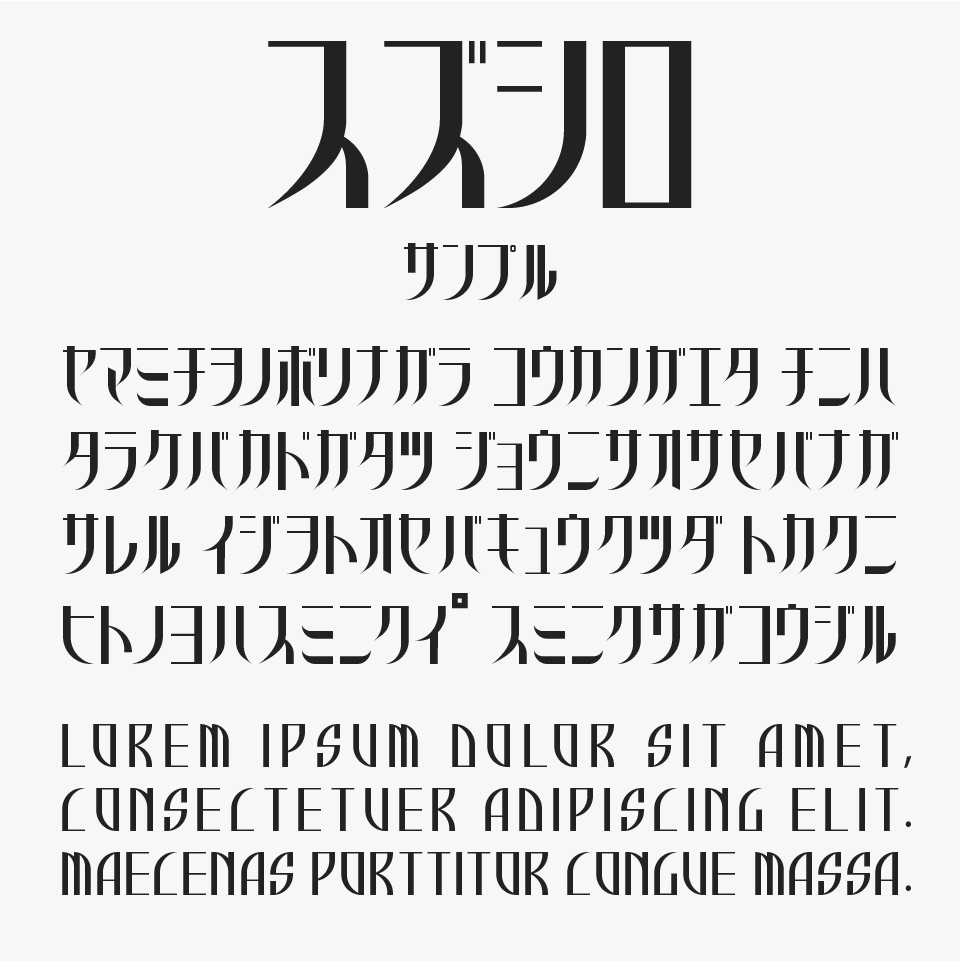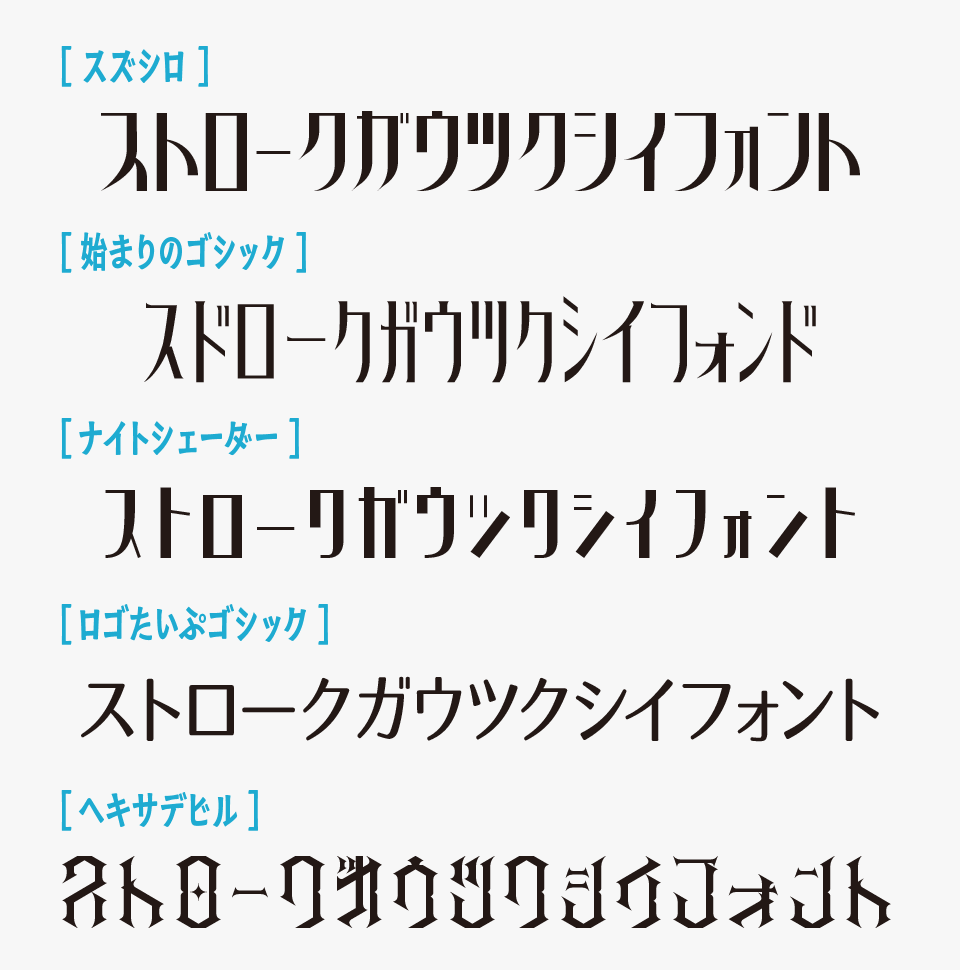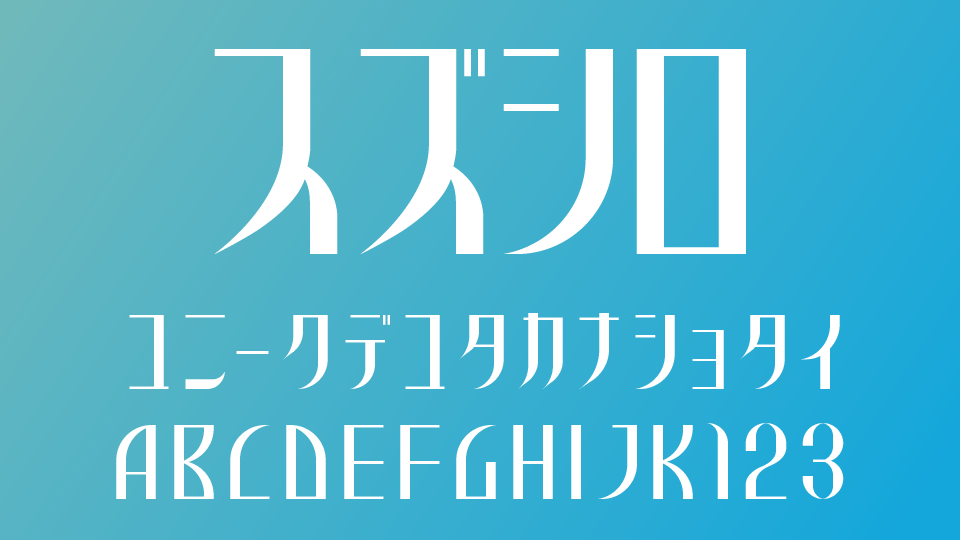
スズシロフォントは、シャープで縦長のプロポーションと鋭い切れ込みが特徴的な、アールデコ調の雰囲気を感じさせるデザインフォントです。
細い線と太い線のコントラストが美しく、文字全体に洗練された雰囲気を感じられるフォントです。幾何学的でありながらどこか優雅さもあり、クラシカルな空気と未来的な印象がミックスされたようなデザインがとてもステキです。
映画タイトルや漫画ロゴや高級感のあるパッケージ、レトロモダンなビジュアルなどと相性が良く、フォントそのものでロゴが完成してしまうようなフォントです。都会的でミステリアスな空気をまとった、個性的なフォントです。
スズシロフォントを、ほかのシャープなスタイルを持つカタカナフォントと比較してみると、鋭さの中にある軽やかさや洗練された雰囲気が魅力のフォントです。
比較フォントは、「始まりゴシック」「ナイトシェーダー」「ロゴたいぷゴシック」「ヘキサデビル」と使用していますが、どれもストロークがシャープでカッコいいフォントなので、ぜひあわせてチェックしてみてください。